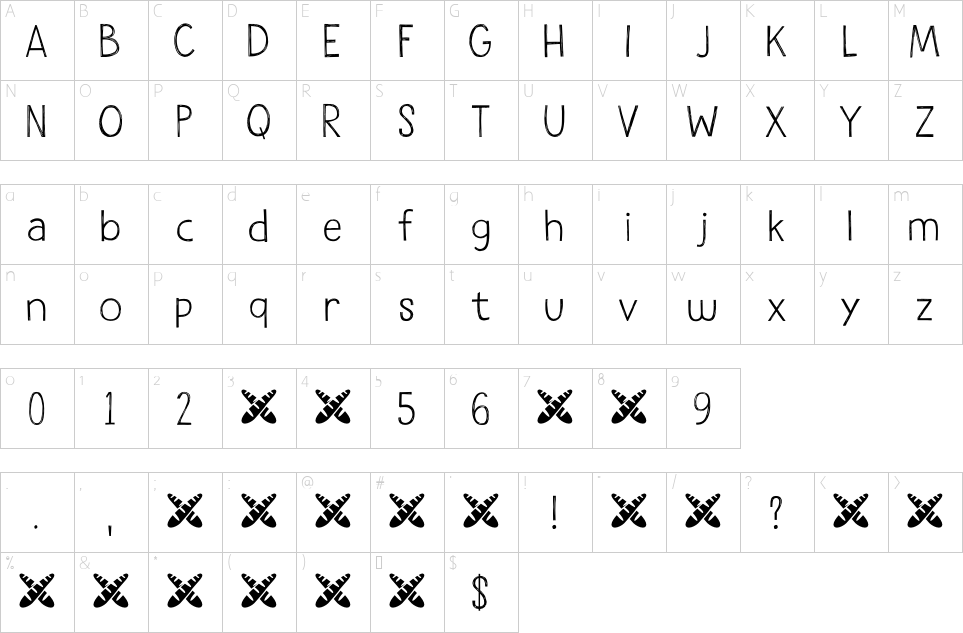
Descubra a fonte Machin em sua coleção de 1001 Free Fonts, uma fonte minimalista e elegante projetada por Hanoded. Machin é perfeito para textos de design gráfico, apresentações e até mesmo para criar mensagens pessoais com um toque moderno. Com seu design limpo e agradável ao olho, Machin encaixa-se perfeitamente em qualquer projeto, seja ele para web, impressão ou aplicativos. Recentemente, Machin foi baixado 119 vezes, demonstrando seu valor e popularidade. Se você está procurando por uma fonte moderna e versátil que não comprometa sua criatividade, Machin é uma ótima escolha. Baixe-a agora e faça seus projetos brilharem ainda mais.